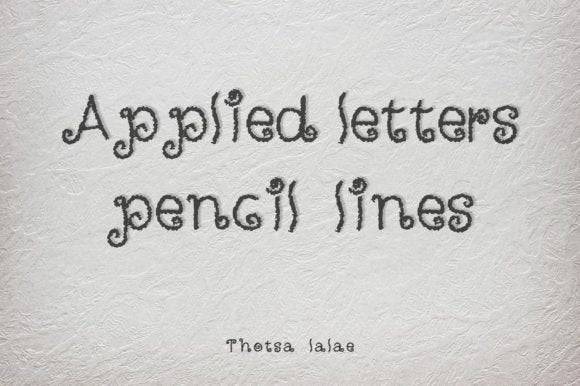
Fonte Applied Letters para títulos, pôsteres e projetos de identidade visual.
A fonte Applied Letters foi criada com a técnica de desenho à mão a lápis. Possui um toque vintage e lembra caracteres da antiguidade, como os encontrados inscritos em mapas ou baús de tesouro. É adorável e única.